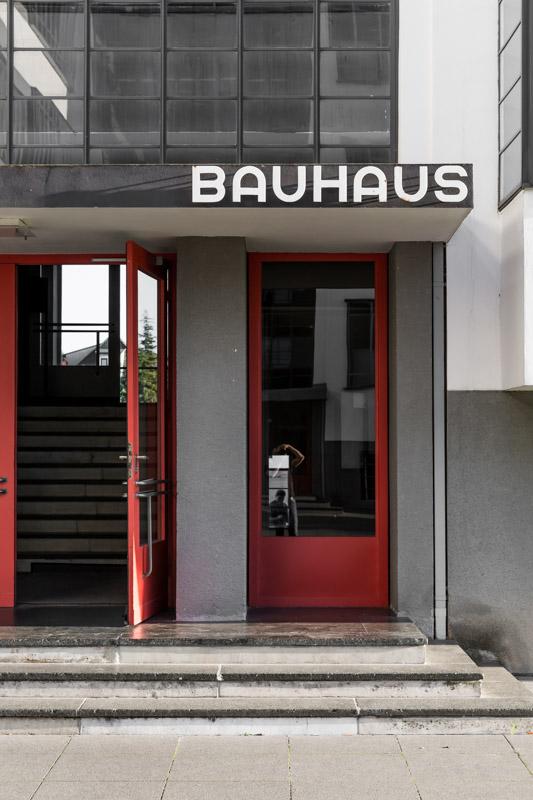
Hallo, ich suche seit Stunden die Schrift des Bauhaus Gebäudes in Dessau. Alles was unter Bauhaus oder Herbert Bayer angeboten wird hat damit nichts zu tun. Es handelt sich um VERSALIEN mit einem charakteristisch tief liegendem Querstrich im A und um einem annähernd quadratischem Grundriss jedes einzelnen Buchstabens. Danke für Hinweise!